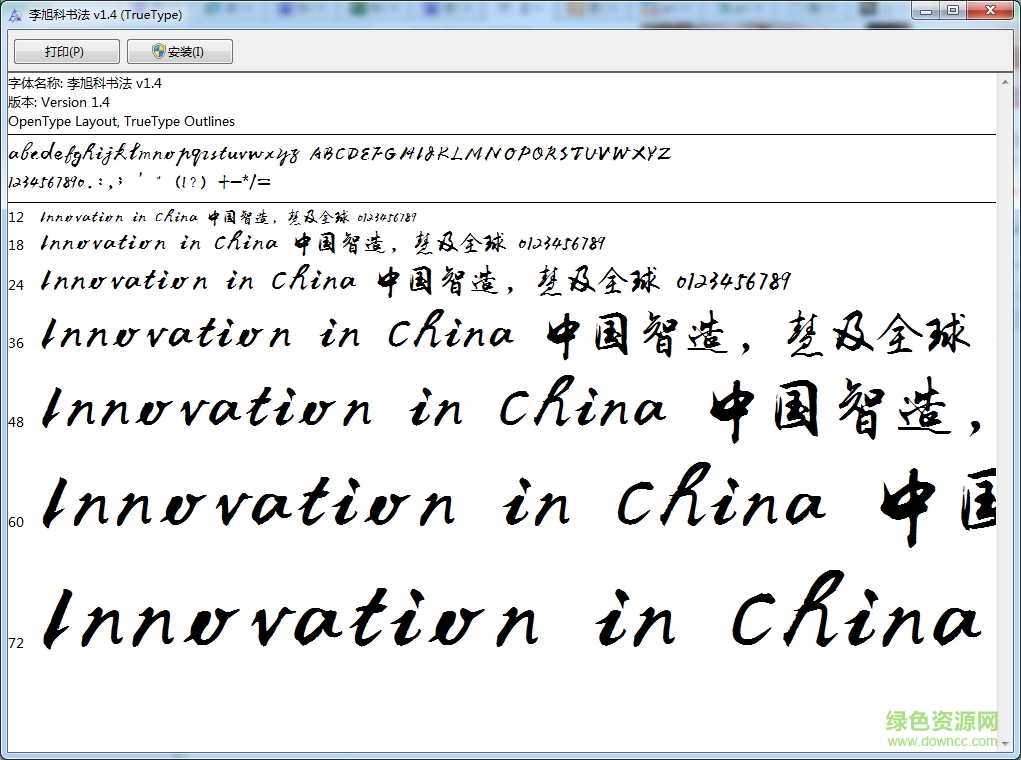
李旭科書法v1.4是一款非常好用的書法字體,字體粗細(xì)適中,廣泛應(yīng)用于美工設(shè)計(jì)、圖文印刷、海報(bào)宣傳等多種行業(yè),使用簡單時(shí)刻彰顯個(gè)性??靵砭G色資源網(wǎng)下載體驗(yàn)吧!
李旭科書法是書法家李旭科書寫的一套字體,字體飄逸,適合喜歡書法的朋友臨摹研究,也適合廣告、網(wǎng)頁等設(shè)計(jì)人員用作字體設(shè)計(jì);需要的朋友不要錯(cuò)過。